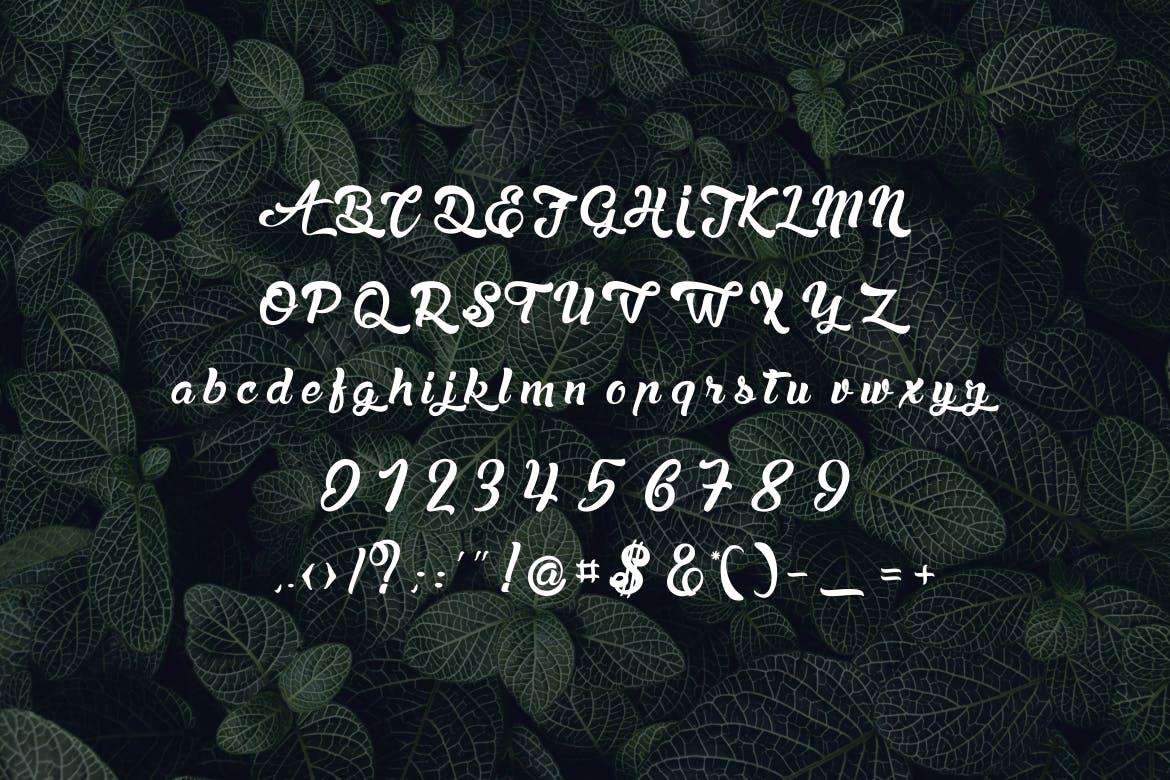
فونت Dengal یک گزینه بینظیر برای پروژههای آینده شماست.
این فونت برای طراحیهای مدرن، برندینگ، طراحی لوازم تحریر، طراحی وبلاگ، تبلیغات مدرن، دعوتنامهها، نقل قولهای هنری، دکوراسیون منزل، عناوین کتاب و جلد، رویدادهای خاص (ازدواج، تولد و...) و هر نوع طراحی مدرن و شیک دیگر بسیار مناسب است.